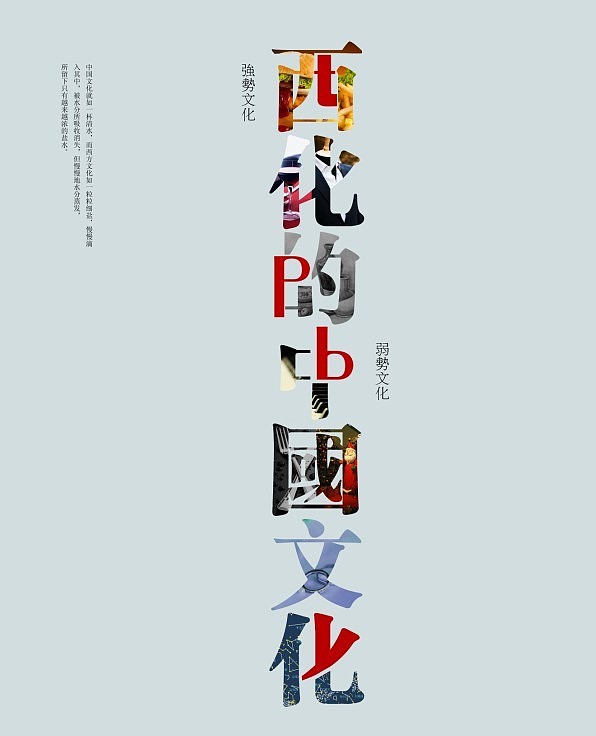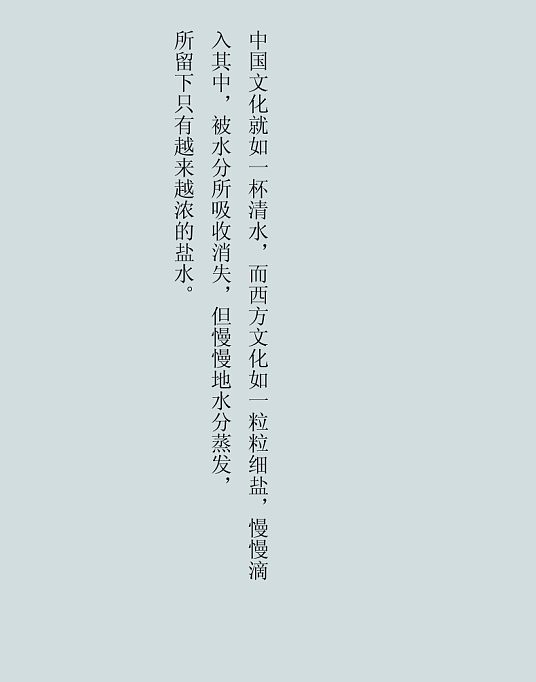
“西化的中国文化”毕业设计标题初稿
现在看到中国文化中夹渣着许多西方文化,而身在其中的我们却一直不知不觉的吸取着这些文化 因此想通过这个设计唤起大家对正统的中国文化的了解与保护
标题设计使用的是 标题宋体 其他特意把一些中文的笔画 转变成英文字母,想凸显西化的概念,而文字中填充的各类图片,是为了传达“虽然我们留有中国文化的框架,但其中的内容已经渐渐地转变”的含义